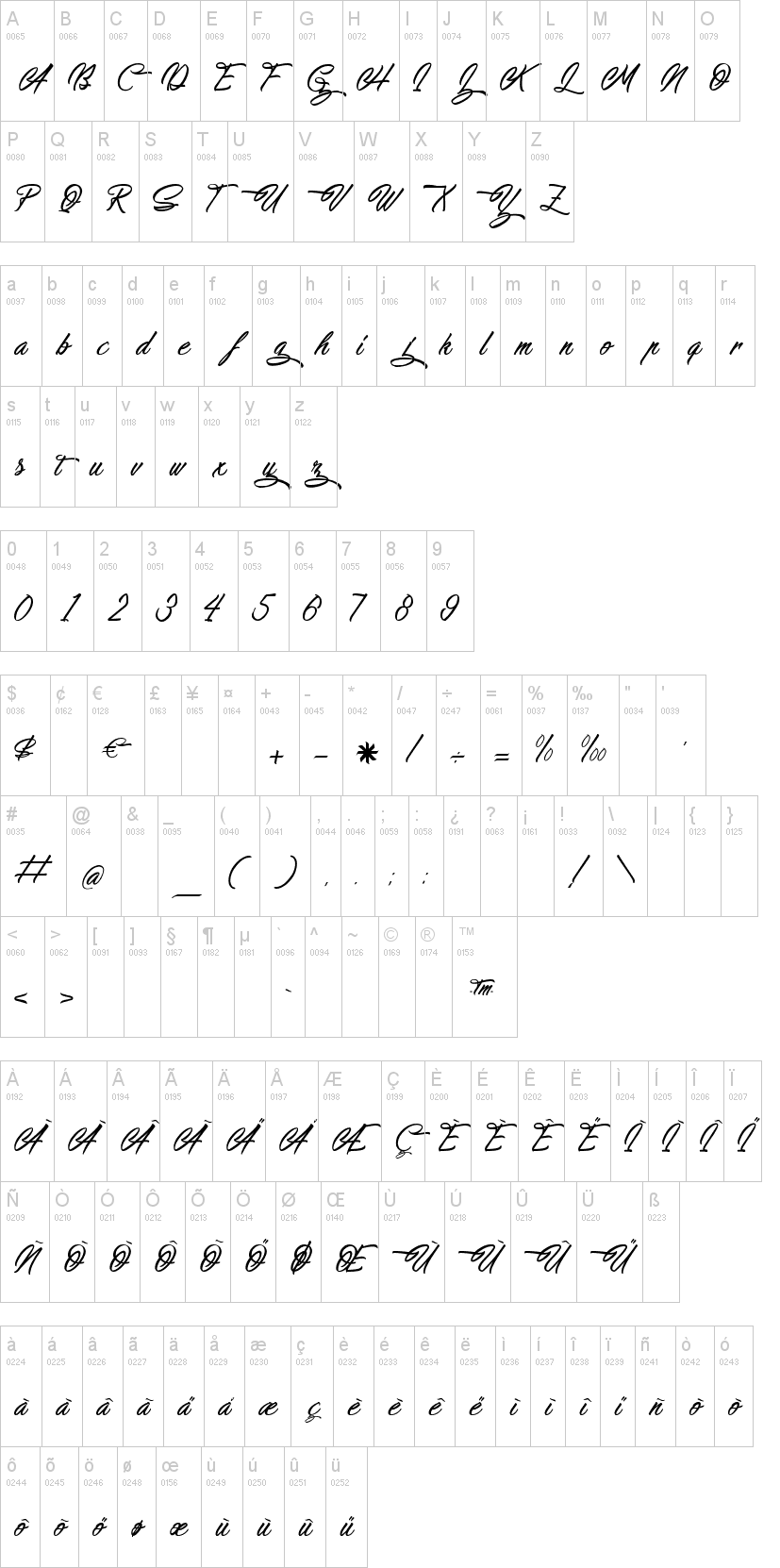
吗? Walking in Sunlight 是一款具有活力的手写字体,由设计师Nina Stössinger设计。它的特点是拥有明亮的颜色,简洁的曲线,以及柔和的笔触。它可以用于标题,标语,标签,品牌标识,广告,卡通,印刷,网站,和其他设计。它的外观活泼可爱,可以轻松地吸引人们的注意力,从而使设计更加有趣。内容介绍
Walking in Sunlight是一款非常不错的手写艺术字体,具有很好的视觉感,适合于文化类的宣传设计、商业类品牌的广告和产品包装设计以及个性化文字排版等较多场景。